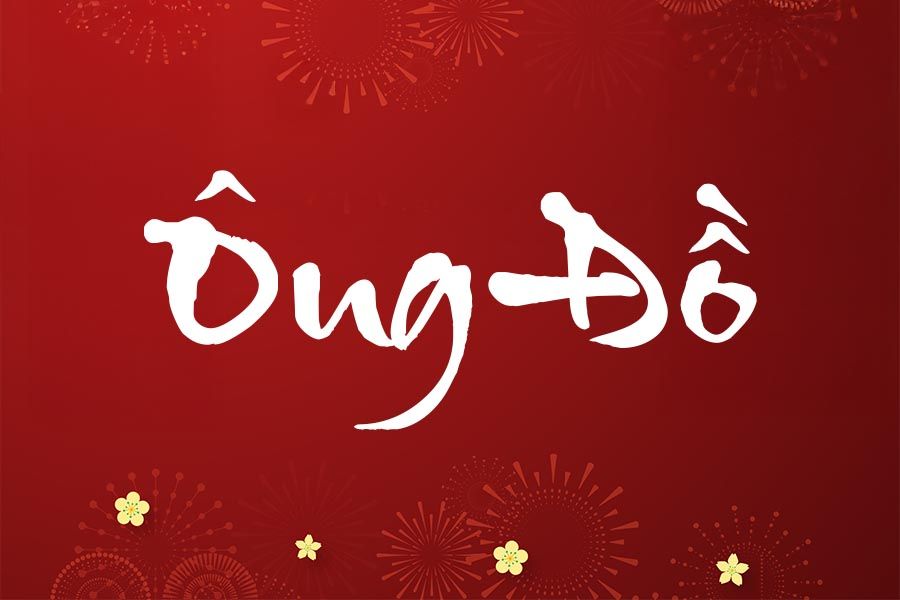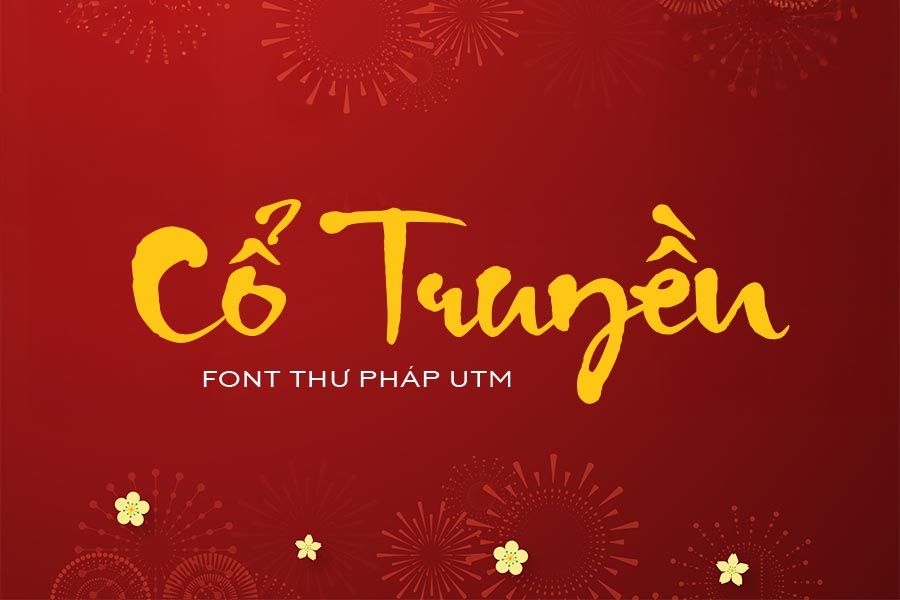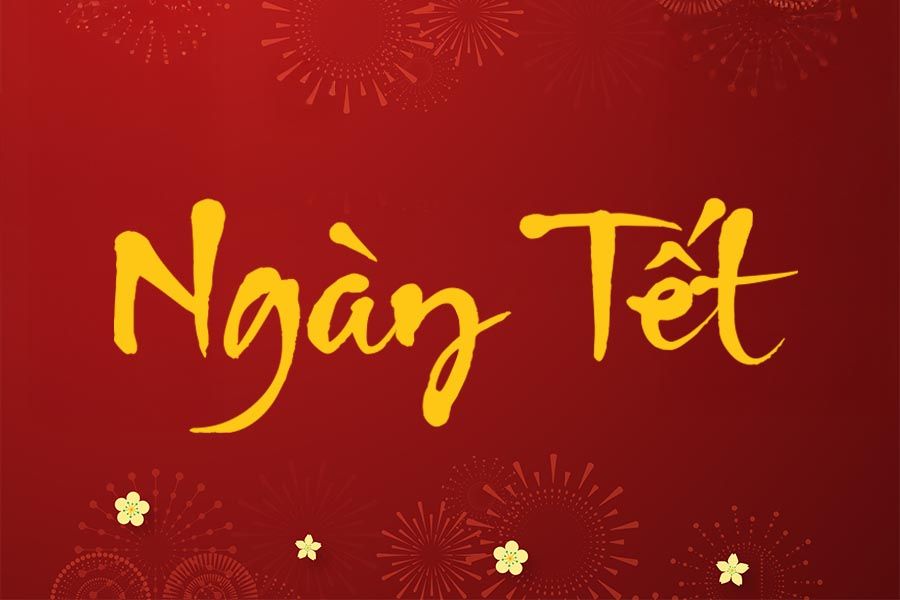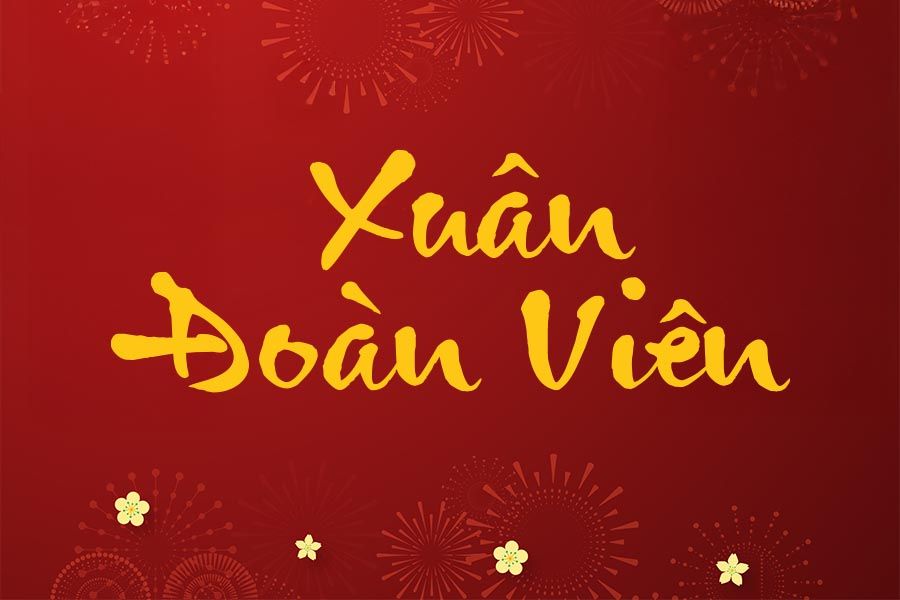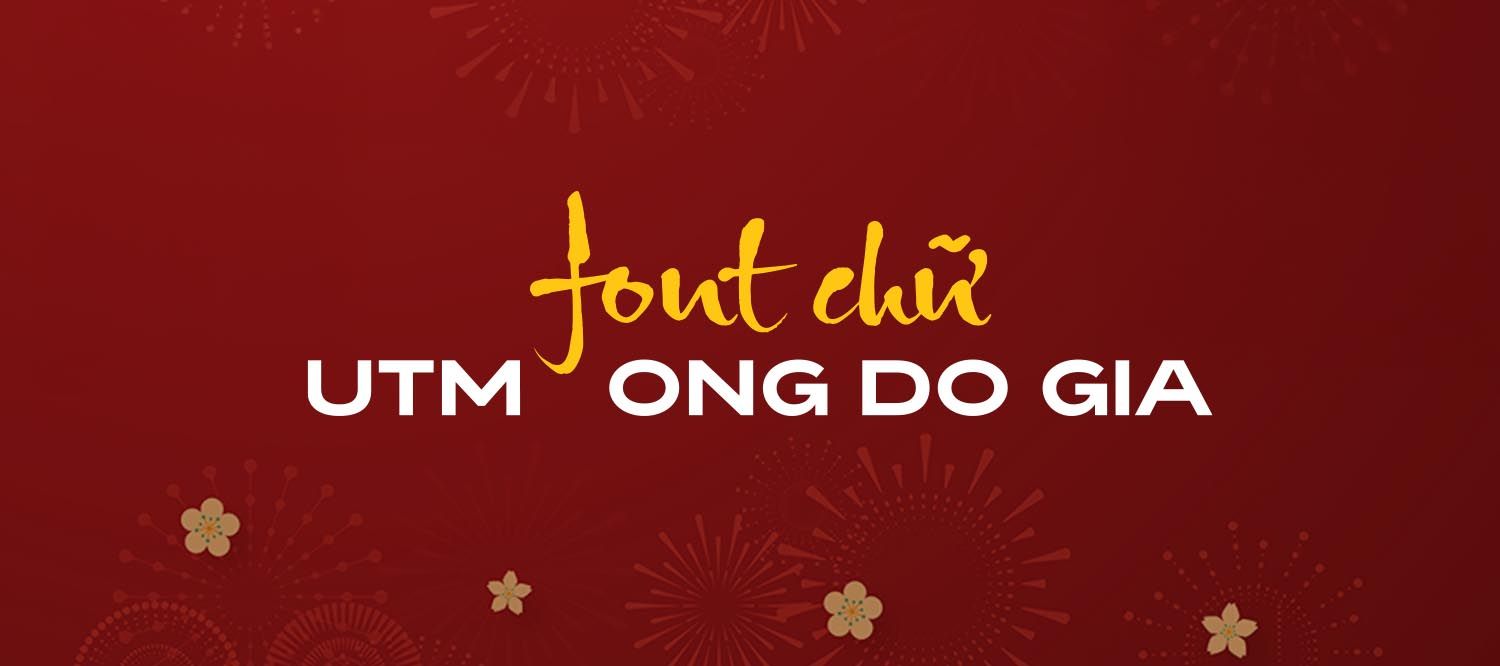
Font chữ UTM Ong Do Gia là một trong những lựa chọn không thể thiếu cho những ai yêu thích vẻ đẹp truyền thống của thư pháp Việt. Mang đậm phong cách ông đồ viết câu đối đỏ, font chữ này không chỉ thể hiện tinh thần dân tộc mà còn giúp các nhà thiết kế truyền tải thông điệp văn hóa sâu sắc trong các ấn phẩm mừng xuân, lễ Tết và sự kiện truyền thống. Trong bài viết này, hãy cùng tìm hiểu chi tiết về font chữ UTM Ong Do Gia – một tuyệt phẩm font thư pháp Việt hóa không thể bỏ qua.
UTM Ong Do Gia là một font chữ thư pháp thuộc bộ sưu tập font Việt hóa của Urban Type Management (UTM) – nhóm phát triển nổi tiếng trong cộng đồng thiết kế với nhiều bộ font hỗ trợ tiếng Việt chất lượng cao. Đây là font chữ mô phỏng nét bút lông mềm mại, với cách đi nét bay bổng, biến tấu tinh tế như những dòng chữ được viết từ tay của các ông đồ xưa trong ngày Tết.
Với kiểu dáng gần gũi và quen thuộc với người Việt, font chữ này mang đến cảm giác ấm cúng, hoài cổ, tái hiện không khí xuân truyền thống mỗi khi xuất hiện trong thiết kế.
Font chữ UTM Ong Do Gia được thiết kế theo lối viết tay thư pháp, gợi nhớ hình ảnh câu đối đỏ ngày xuân. Mỗi ký tự đều được tạo dựng với đường cong uốn lượn mềm mại nhưng vẫn giữ độ mạnh mẽ, khỏe khoắn của bút lông.
Khác với nhiều font thư pháp lấy cảm hứng từ chữ Hán, UTM Ong Do Gia kết hợp hài hòa giữa chữ quốc ngữ và nghệ thuật thư pháp, tạo nên một phong cách rất riêng – thuần Việt, mộc mạc và gần gũi.
UTM Ong Do Gia là lựa chọn hàng đầu trong các thiết kế mang chủ đề truyền thống. Dưới đây là một số ví dụ tiêu biểu:
Thiết kế poster Tết, bao lì xì, banner chúc mừng năm mới
In ấn câu đối đỏ, thiệp chúc xuân, chữ treo tường
Trang trí gian hàng Tết, lễ hội văn hóa dân gian
Dự án truyền thông, video clip, intro mang âm hưởng dân tộc
Bìa sách lịch sử, thơ ca, truyện cổ tích
Font giúp truyền tải cảm xúc cổ kính, gợi nhắc không gian văn hóa xưa với ông đồ ngồi viết chữ giữa phố xuân, vừa sang trọng vừa thân quen.
Không cần thêm hiệu ứng rườm rà, chỉ riêng font UTM Ong Do Gia cũng đủ tạo nên không khí Tết cổ truyền nhờ hình dáng chữ đặc trưng.
UTM Ong Do Gia không chỉ là một font chữ thư pháp đẹp mắt, mà còn là cầu nối văn hóa giúp truyền tải tinh thần Tết Việt vào từng thiết kế. Với phong cách ông đồ hoài niệm, font này xứng đáng có mặt trong bộ sưu tập font của bất kỳ ai yêu cái đẹp truyền thống và muốn tạo dấu ấn riêng trong thiết kế.